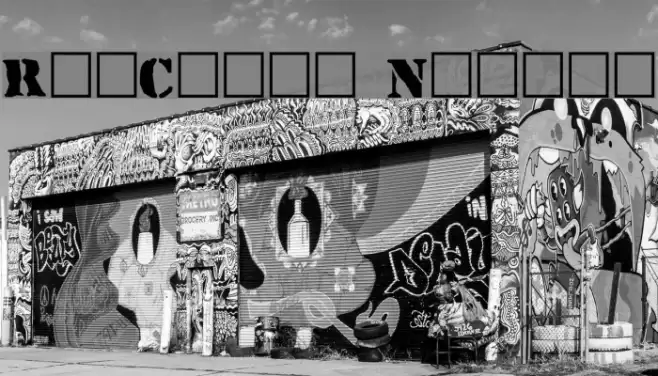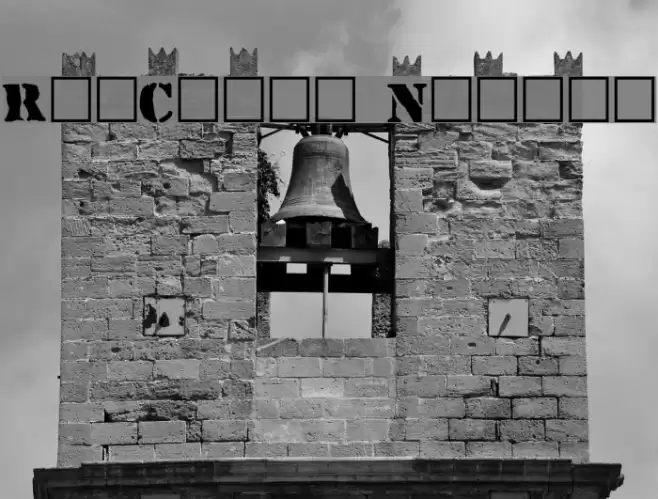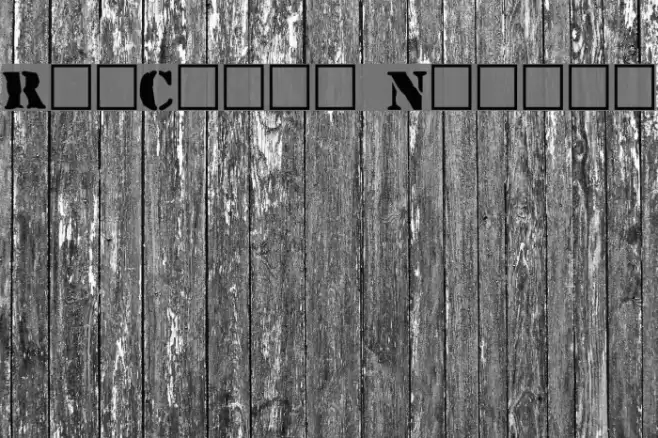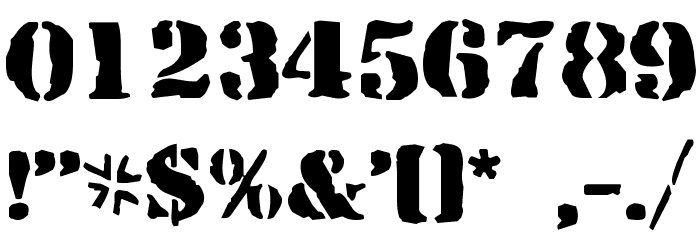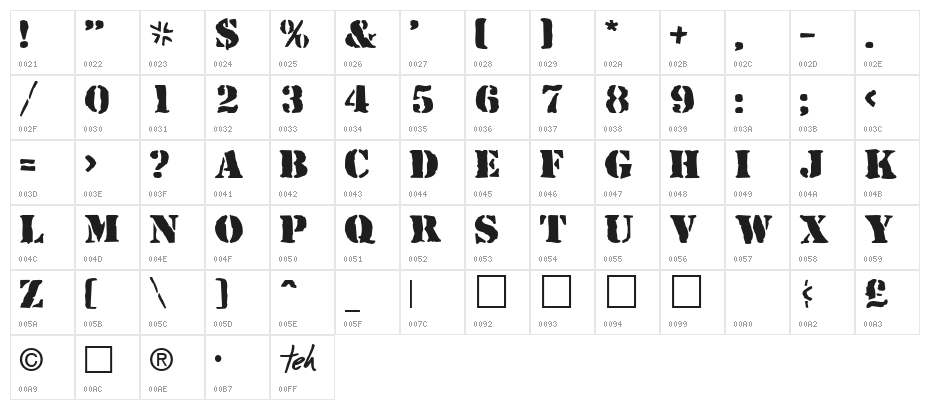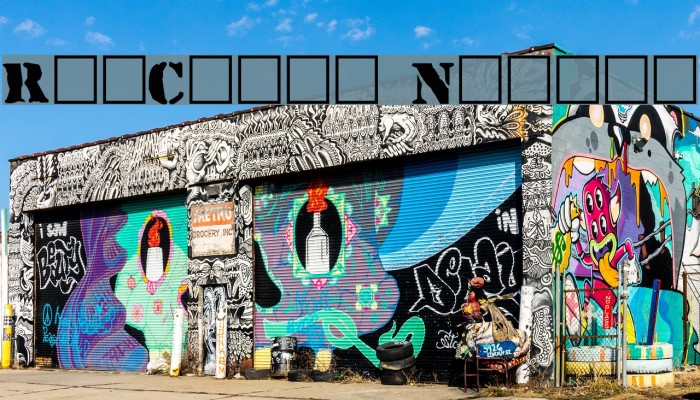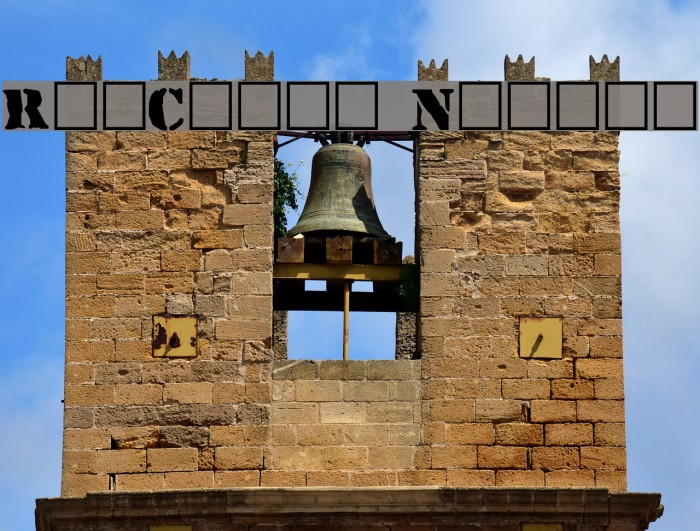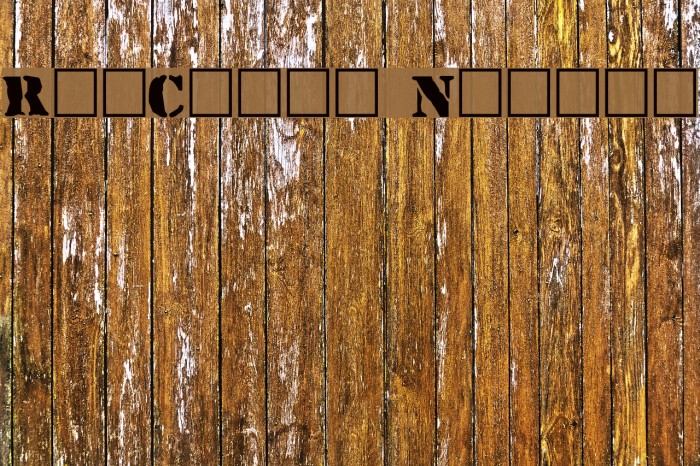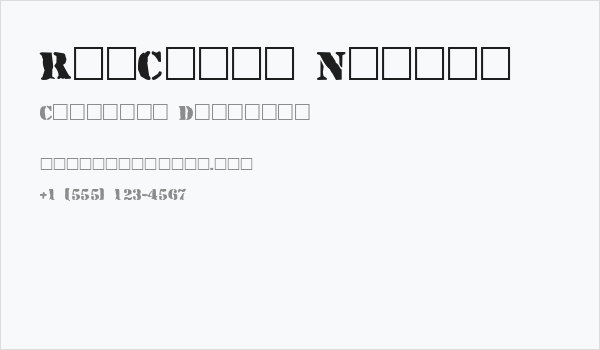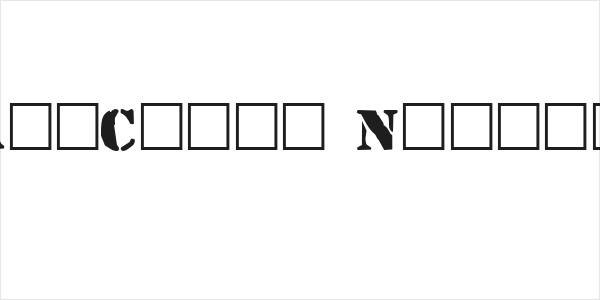
RufCrate Normal Font
Espacement des caractèresMonospaced
ContrasteMedium
Style généralIndustrial, Stencil
Cas d'utilisationLogos, Posters, Signage
Projets proposésIdeal for use in military-themed designs, industrial branding, posters, and signage that require a bold and impactful presence.